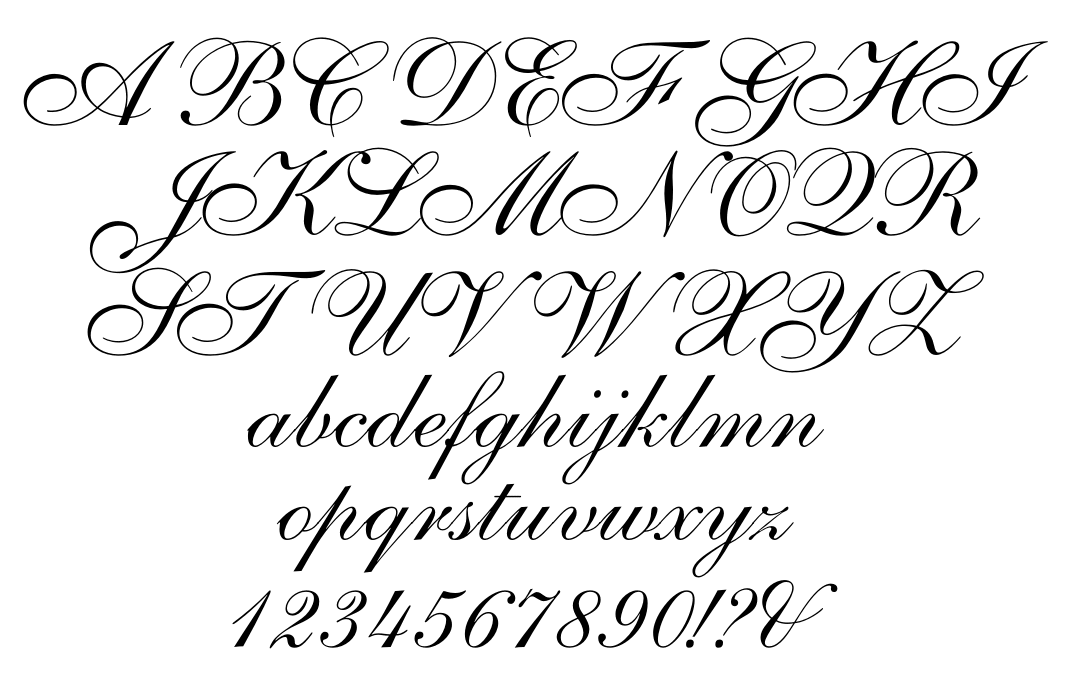
Шрифты в web-дизайне
Шрифты в web-дизайне- начертание: прямой, курсивный (свойство font-style)
- насыщенность: светлый, полужирный, жирный (свойство font-weight)
- ширина: нормальный, узкий, широкий (свойство font-stretch), шрифт фиксированной ширины (моноширинный)
- размер (кегль) – высота литер шрифта (свойства font-size, font-size-adjust)
- наличие (serif) или отсутствие (sans-serif) засечек на концах линий. Это группы шрифтов Антиква, с засечками и Гротеск, без засечек:
Семейства шрифтов (свойство font-family)
- Шрифты с засечками, или антиква (font-family: serif):
- Times Georgia (шрифт Georgia)
- Times Georgia (шрифт Times New Roman)
- Шрифты без засечек, рубленые шрифты, или гротески (font-family: sans-serif)
- Arial, Helvetica
- Tahoma, Geneva
- Моноширинные шрифты, когда все знаки имеют одинаковую ширину (font-family: monospace)
- Courier New, Courier
- Lucida Console, Monaco
- Шрифты, имитирующие почерк (font-family: cursive)
- Comic Sans MS, Comic Sans, cursive
- Bradley Hand, cursive
- Декоративные шрифты, для названий и т.
д. (font-family: fantasy) - Impact, fantasy
- Luminari, fantasy
Много и разные.
- %, процент.
- cm, сантиметр.
- px, пиксель (от picture element). Используй для указания размеров элементов макета: блоков, изображений.
- em (название связано с шириной заглавной M) – относительная единица измерения, равная текущему указанному размеру шрифта. Спецсимвол HTML — имеет ширину в 1 em: «—». Используй для указания размеров шрифта!
- rem (от root em). 1 rem равен вычисленному значению font-size главного элемента. Используй для указания размеров шрифта!
- pt, пункт (desktop publishing point). Равен 1⁄72 дюйма, или 0.353 мм. Используется в Microsoft Word как основная единица. Не используй в web-страницах!.
Как устроено свойство font-size (размер шрифта) в CSS
- font-size наследуется по всему дереву документа
- Если нигде не было определено свойство font-size, то значение единичного em будет равно 16px, которое является значением по умолчанию
Подробнее о единицах размера и об их применении для шрифтов на сайте Консорциума Всемирной паутины (по-русски).
Переносы строк и тег pre
- Для сохранения переносов строк используется тег <pre> или свойство white-space: pre
- Для тега pre по умолчанию установлен моноширинный шрифт: font-family: monospace.
Шрифты для латинского алфавита
то есть он готовит КОИ8-Р вариант той же страницы.
д. (font-family: fantasy)